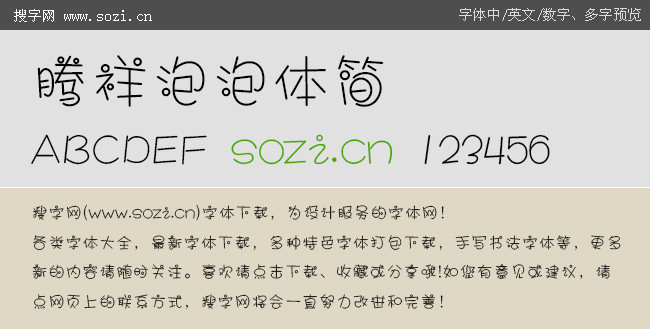
騰祥泡泡體簡(jiǎn)
搜字網(wǎng)提供一款騰祥泡泡體簡(jiǎn)中文字體下載, 騰祥泡泡體簡(jiǎn)是騰祥字庫(kù)全新開發(fā)的一款非常不錯(cuò)的美術(shù)字,該字體書寫筆畫隨意放松,富于變化,充滿卡通趣味極富裝飾色彩,能夠適用于藝術(shù)設(shè)計(jì)、包裝印刷、簽名設(shè)計(jì)、圖形設(shè)計(jì)等領(lǐng)域。(此款為個(gè)人非商用版,如需商用請(qǐng)聯(lián)系騰祥字庫(kù)購(gòu)買)